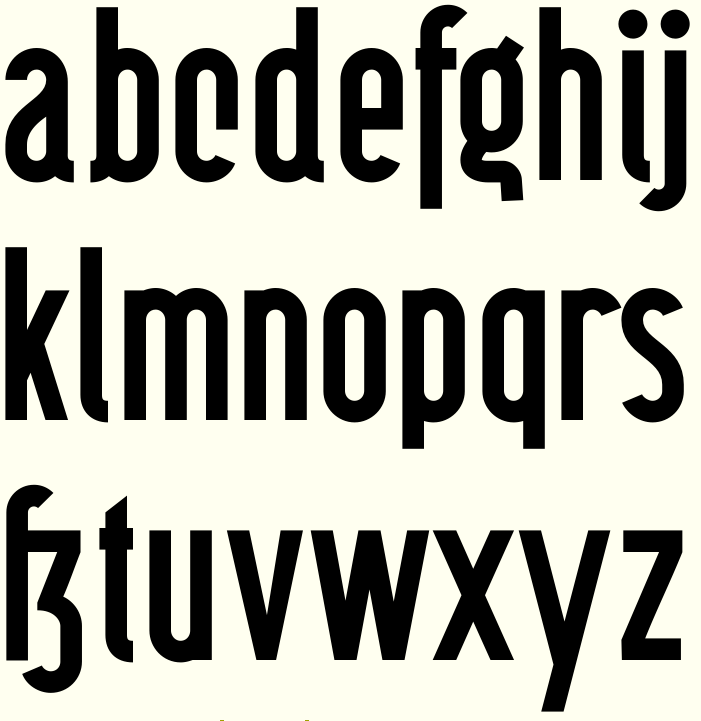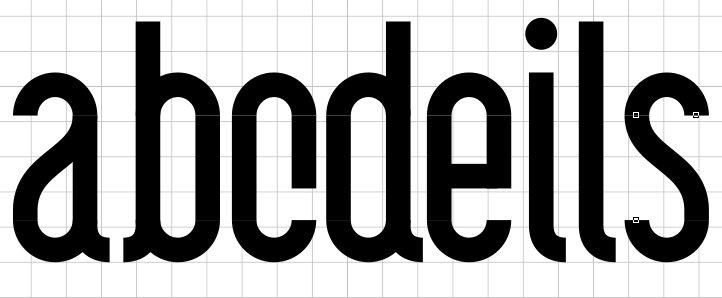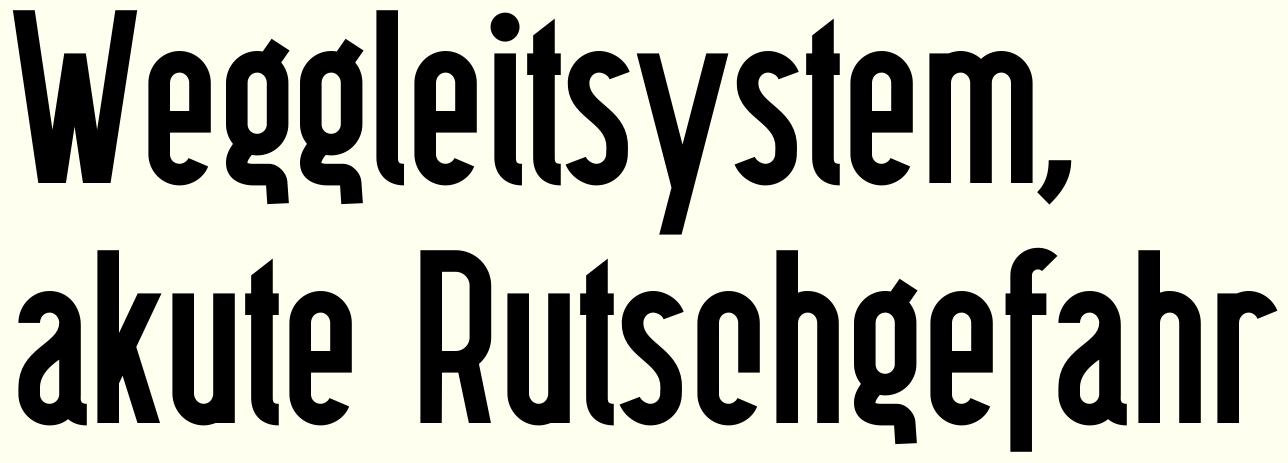
Suche diese Schrift eines Berliner Eiswerk-Transporter
Ich arbeite gerade an einem Weggleitsystem für das renovierte Berliner Eiswerk in der Köpenicker Straße. In den Unterlagen habe ich dieses Foto gefunden und finde die Schrift klasse. Würde sie gerne nutzen wollen, um die "Historische-Aura" des Werkes weiter leben zu lassen. Außerdem ist das "l", "c", "5" und "6" recht einzigartig.
Kann mir jemand helfen? Oder mir einen Tipp geben, wie ich weiter suchen könnte?
PS: So die Schrift wird wahrscheinlich selbt gemalt sein. Kennt ihr zumindest eine  schrift mit ähnlichen Merkmalen der benannt, interessanten Buchstaben?
Vielleicht kommt das Dir ja schon recht:
Das sehr spezielle c möchte ich fast als "Berliner c" bezeichnen, bei dem das c praktisch die Schablone auch für das e ist, sodass nur noch ein waagerechter Strich hinzugefügt werden muss. Ich habe es auch in Wandanschriften von Berliner Bunkerwänden gesehen.
l mit Häkchen, f mit Unterlänge und deine 2 (3) speziellen Ziffern hat sie zwar nicht, aber wenn es unbedingt erforderlich ist...
In diesem Zusammenhang habe ich meine Sammlung von Schriftvorlagen-Bildern noch einmal durch gesehen. Einige der Bilder stammen aus verschiedenen Strängen hier.
Da die "Berlin Email", abgesehen vom C,  leider doch recht unterschiedlich zur Referenz ist, hätte ich doch noch eine Frage:
Gibt es EDV-Schriften von den Schriften auf den Schildern, welche Sie nachgelegt haben?
Noch nicht, aber aus gegebenem Anlass bin ich sogar gerade dabei. Das wird dann wahrscheinlich nicht eine bestimmte der Schilder (und der Stangeneis-Produzenten sein, sondern ein Mix aus allen, so z.B. mit dem g aus der "Stiege" den kleinen Häkchen unten bei i und l sowie als Sporn bei a, b, p, q, d usw.,  Unterlaängen bei f und ſ, vielleicht ein N ähnlich wie in "Nicht sprechen" (natürlich ohne die Pinselrundung)  (es sei denn, es gäbe noch mehr Originalmaterial aus der Eisfabrik.
Hier schon mal die ersten Buchstaben:
Ich hätte vielleicht noch eine Anmerkungen oder Idee zu deinem Entwurf:  Das Besondere neben den schönen Lettern ist, dass die Schrift (für eine deutsche Schrift) recht bold und sozusagen cool wirkt.  Z.B. sas "S", "s" sieht ja schon recht bold und geschlossen aus. Der ganze Duktus oder Idee der Schrift hat schon etwas von der angehängten Schrift hier. http://dia.tv/bespoke/  (auch wenn wirklich alle Details nicht übereinstimmen 🙂).  Also was ich meine, dass die Kontraste recht hoch sind.
An Kerning muss ich aber, wie gesagt noch Arbeiten, Hatte heute nur eben die Satzzeichen soweit fertig bekommen, dass ich es schon mal zeigen kann.
So, ein bisschen nachgefeilt, z.B. y war viel zu breit, Kerning, OpenType-Features, so z.B. Groß-I am Wortanfang mit Haken . innen Glatt in Versalsatz (calt) , 2. ß über ss01, 2. z über ss02, Ligaturen wie in der Lesefreude.
Ein schönes Projekt!
Leider ist die Schrift noch nicht wirklich so, das ich sie vorstellen könnte. Ist ja auch logisch, da professionelle Schriften ja Monate oder Jahre brauchen, um sie zu entwickeln.
Im Anhang liegen die favorisierten Schriften zusammen mit der Berliner Wand.
Um schneller ein brauchbares Ergebnis zu erziehlen würde ich eher die Plaak oder die Gothik Grotesk nehmen und die beschriebenen Buchstaben einfügen und vielleicht da und dort einige Details ändern.
lg fm
Da wurde wohl eine Software ohne Opentype-Unterstützung verwendet - und dann auch wohl nicht die letzte Version?
Ich nutze  Illustrator CC und natürlich die letzte Version
Ich meinte, es war noch "nicht die letzte Version der Schrift", sondern nur die noch unfertige Ur-Version ohne OT-Features. Hatte die ja eigentlich nur gezeigt, um überhaupt die Glyphen zu sehen.
ss01 = "berliner ß" ersetzt durch gewöhnliches ß,
ss02 = z ersetzt durch z mit Unterlänge,
sso3 + calt = ersetzt das gerade I durch das I mit J-Häkchen am Wortanfang - Gilt auch für die I mit Akzent.
Die letzte Änderung mit I als Standard statt des Häkchen-I habe ich für Nutzer ohne OT-Unterstützung eingefügt, denn die hätten das Häkchen-I auch im Veralsatz innen im Wort, wo es schlicht doof ist. Daher tauscht ss03 dann I, Í, Ì, Î durch die Häkchen-Version, calt tauscht das dann im Wortinneren zurück.